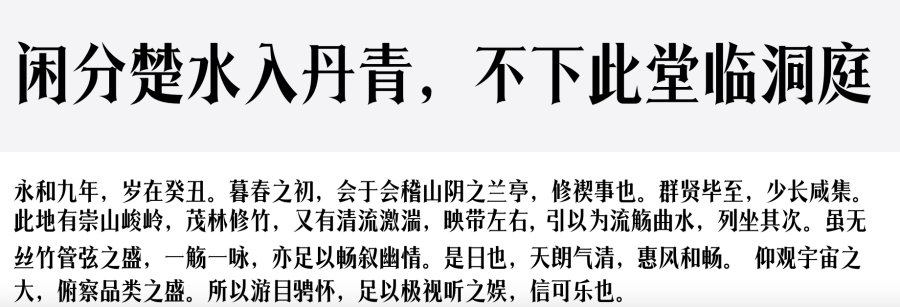
适用于书籍封面排版的字体有哪些?
常用的排版中文字体,用的最多的主要是还是宋体类和黑体类。
宋体其结构饱满、端庄典雅、整齐美观,宋体字非常适用于印刷刻版。
1、上首烈宋体字体拥有古典气质,整体倒圆,闭合位置粗细一致。
上首烈宋体
2、上首国宋体:字体笔画采用较为接近宋体做法,但笔画整体更加大气,直线与曲线交汇,特点是横笔呈直角梯形,笔画整体粗细均匀,整体给人一种稳重踏实的感觉。字体整体柔美稳重但又不大气浑厚
上首国宋体
黑体笔画粗细均等,整体简洁具有分量,也比较适合作为封面排版的标题使用。
黑体字